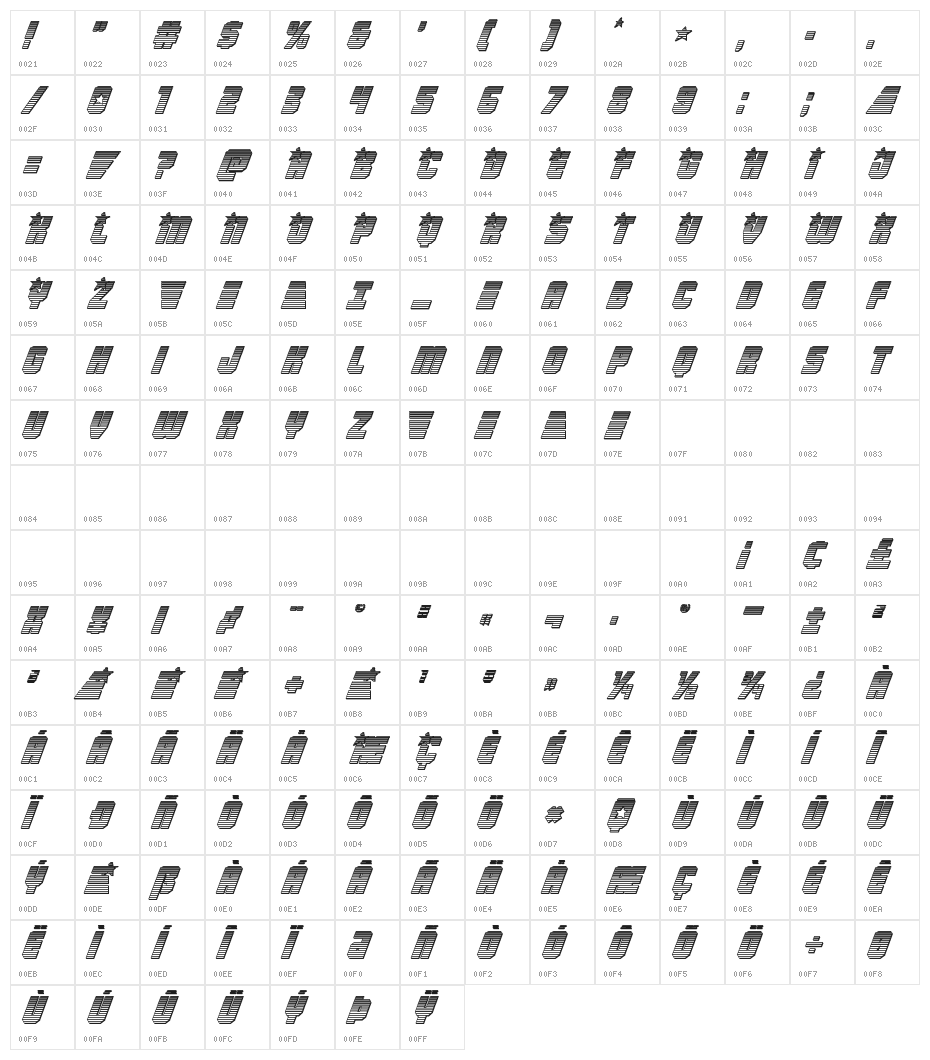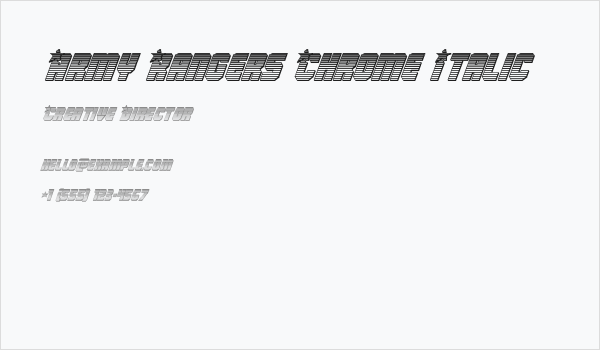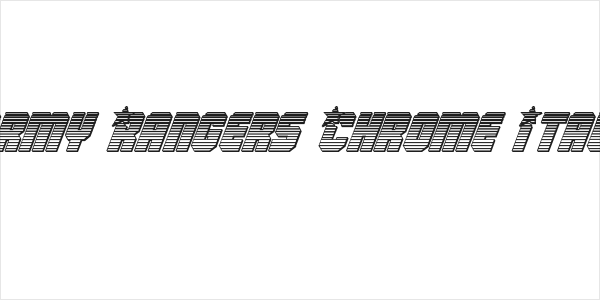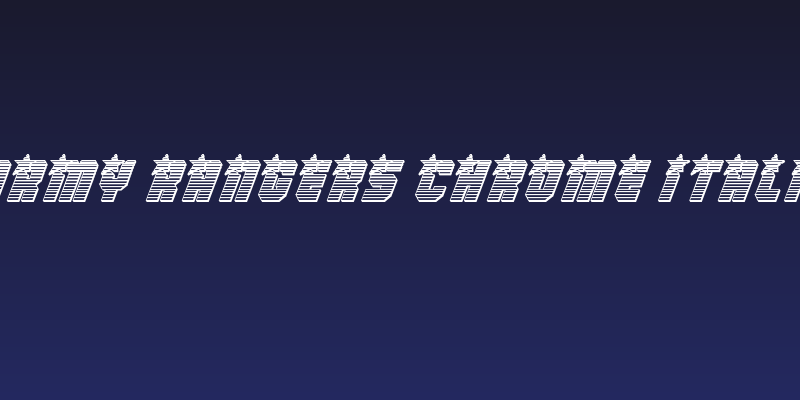
Army Rangers Chrome Italic Font
| Stile generale | Futuristic, Industrial |
| Progetti proposti | Ideal for use in sci-fi themed designs, video game titles, movie posters, or any project requiring a futuristic and bold aesthetic. |